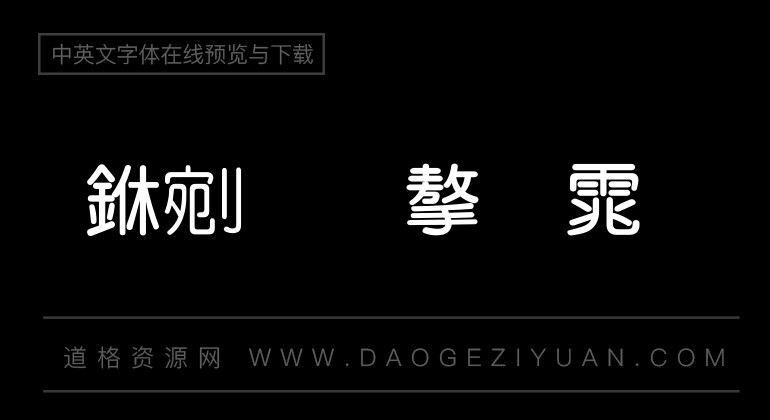
书法家中圆体
书法家中圆体字体,又称“中圆”,是一种中国书法的字体风格。它的特点是圆润、柔和,笔画细腻、曲线优美,笔画宽度基本一致,笔画之间的角度自然,笔法清丽,具有极强的美感,是书法家们最喜欢的字体之一。中圆字体也是绘画书法的常用字体,它的笔画流畅,笔画宽度基本一致,具有良好的美感。它的笔画精致,曲线优美,笔画之间的角度自然,笔法清丽,是书法家们最喜欢的字体之一。
书法家中圆体是一款非常不错的手写艺术字体,具有很好的视觉感,适合于文化类的宣传设计、商业类品牌的广告和产品包装设计以及个性化文字排版等较多场景。